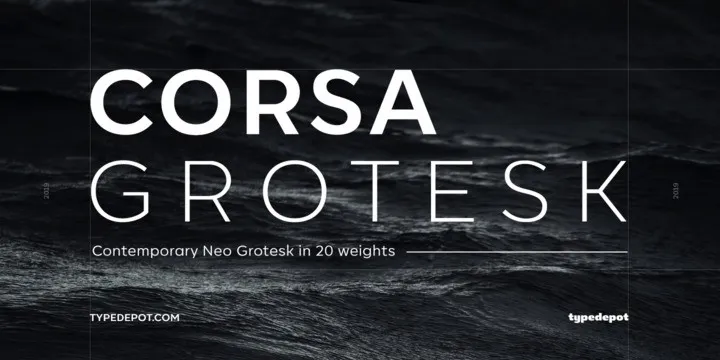
Corsa Grotesk Font Family
Aqui está uma versão em português do Brasil de 2 parágrafos curtos para a descrição da font Corsa Grotesk Font Family: Descobrimos mais um brilho na ampla e original coleção tipográfica do Typedepot: Corsa Grotesk. Inspirada no clássico Avenir, mas com uma visão mais moderna para os designs “Linear Sans” e “Grotesque”, a Corsa Grotesk traz uma nova dimensão à sua biblioteca de fontes. Sua elegância contemporânea e simplicidade geométrica tornam essa família de fontes uma escolha perfeita para aplicativos digitais, websites, logotipos e materiais impressos. Com um design minimalista que se adequa a qualquer layout, Corsa Grotesk é uma escolha versátil para quem busca estilização sem excesso. Sinta-se convidado a explorar essa nova fonte, capaz de capturar o espírito da modernidade em seu projeto. Aproveite a oportunidade de adicionar um toque único e dinâmico à sua composição visual com Corsa Grotesk Font Family.